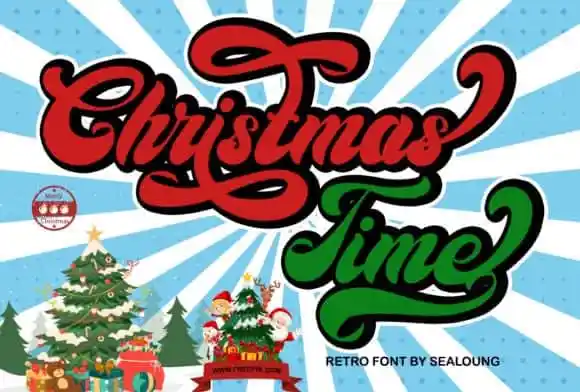
Christmas Time Script Font – Download Grátis
Christmas Time Script Font é uma elegante tipografia script que foi especialmente concebida para a criação de logotipos. Esta fonte foi projetada por Sealoung, com um estilo retro e um toque quente, ideal para aplicar em diversas formas formais como convites, rótulos, logos, revistas e livros. Seus traços fortes e fluidos trazem uma atmosfera festiva perfeita para uso em cartas de cumprimentos ou até mesmo em embalagens de produtos fashion. Com o seu charme único, este tipo de fonte é perfeito para qualquer proposta de anúncio ou design gráfico formal.